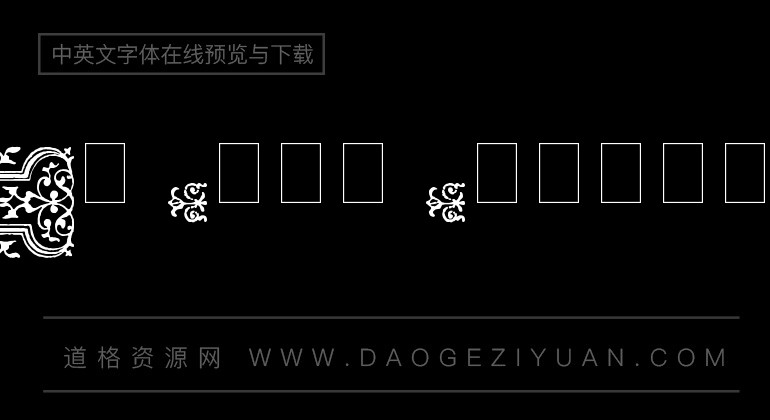
Im Fell Flowers
Im Fell Flowers是一款由美国设计师Ian Fell(伊恩·费尔)创作的花卉字体,它是一种抽象的花卉字体,具有独特的设计风格,具有流畅的线条和清晰的外观。它采用细节精致的花纹,展现出精美的花朵,整体设计极具艺术感,可以用来制作精美的文字设计,也可以用来制作浪漫的花卉图案。
Im Fell Flowers是一款非常不错的手写艺术字体,具有很好的视觉感,适合于文化类的宣传设计、商业类品牌的广告和产品包装设计以及个性化文字排版等较多场景。